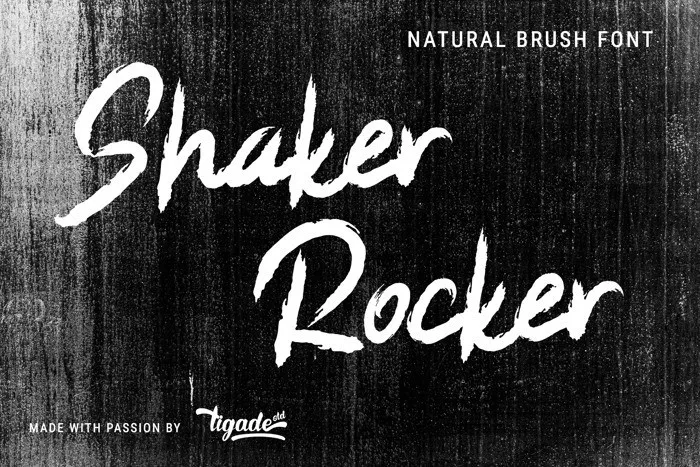
Shaker Rocker Brush Font – Download Grátis
A Shaker Rocker Brush Font é uma tipografia criada à mão inspirada em madeira, árvores e texturas ásperas. Sujeitamente à designer tigade-std, ela se assemelha a posters modernos com toques rústicos, perfeita para o próximo projeto de design. Seu estilo é pura brush-display, perfeito para t-shirts, materiais publicitários, logotipos e qualquer outro tipo de criação que você possa imaginar. Composta à mão, a fonte oferece uma textura única, tornando-a um recurso vital tanto para designers quanto para profissionais do design gráfico. Experimente esta fonte moderna e vibrante para transformar os seus projetos em algo realmente único e encantador.